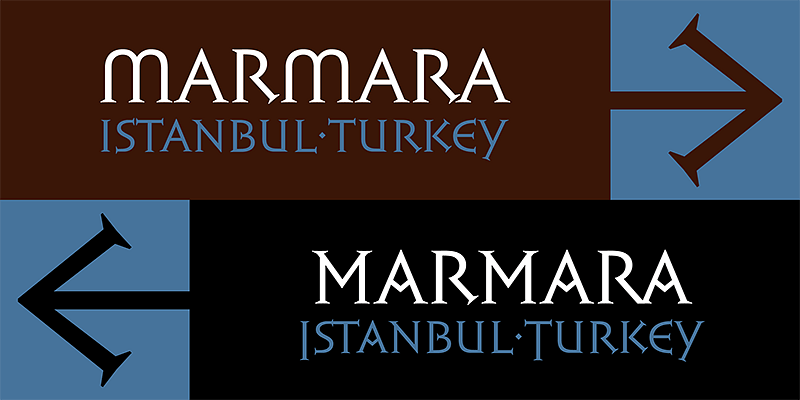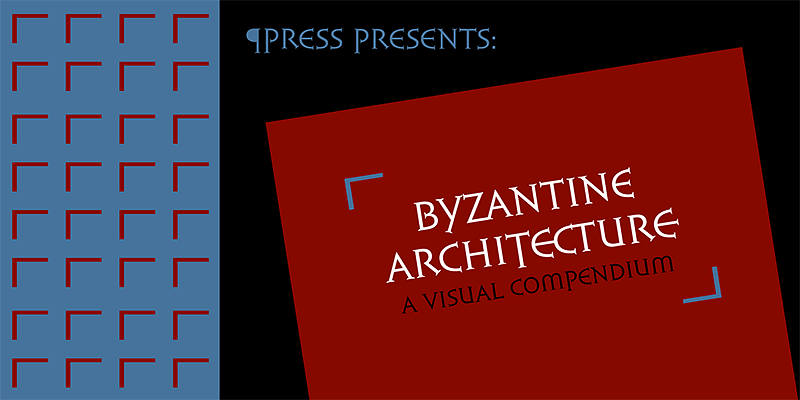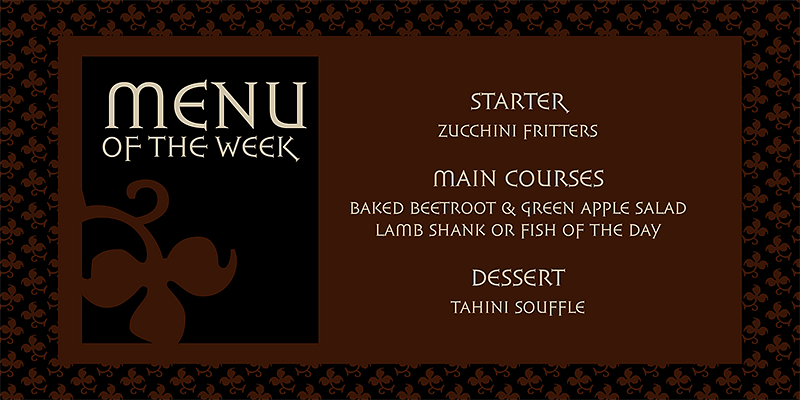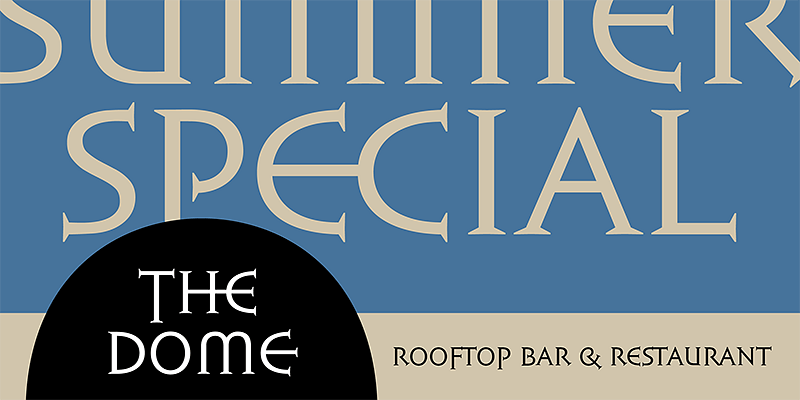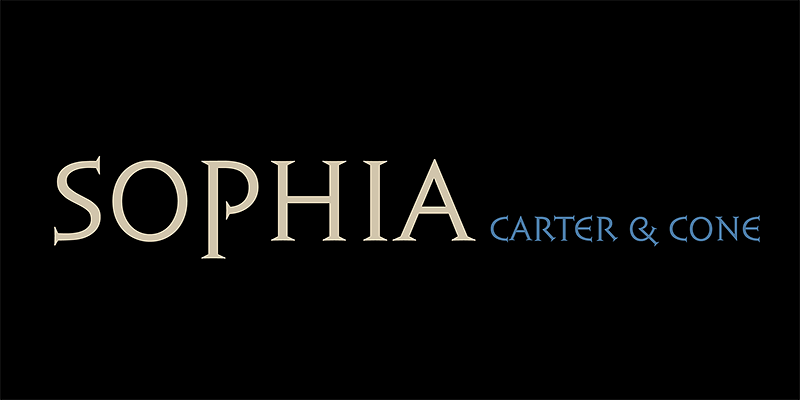
Carter & Cone ha diseñado algunos de los tipos de letra más famosos del mundo y fuentes personalizadas premiadas. Elegante, equilibrada, útil: estos calificativos describen la tipografía producida por la colaboración entre Matthew Carter y Cherie Cone. Aunque sus primeros trabajos constituyen la base de la tipografía moderna, sus tipos de letra más nuevos siguen enriqueciéndola y expandiéndola. La uniformidad y exhaustividad de sus diseños son el resultado directo de una formación temprana en industrias tradicionales, como el punzonado y la caligrafía.